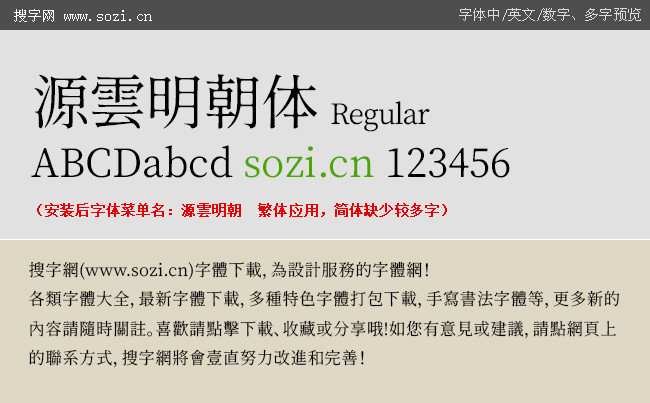
源雲(yún)明朝體Regular
搜字網(wǎng)給大家提供一款源雲(yún)明朝體Regular文字體下載,源雲(yún)明朝體是源自思源宋體的一款繁體中文字體,源雲(yún)明朝體字體粗細(xì)適中,字形端正大方得體。適用于大標(biāo)題、包裝設(shè)計(jì)、海報(bào)設(shè)計(jì)等應(yīng)用。